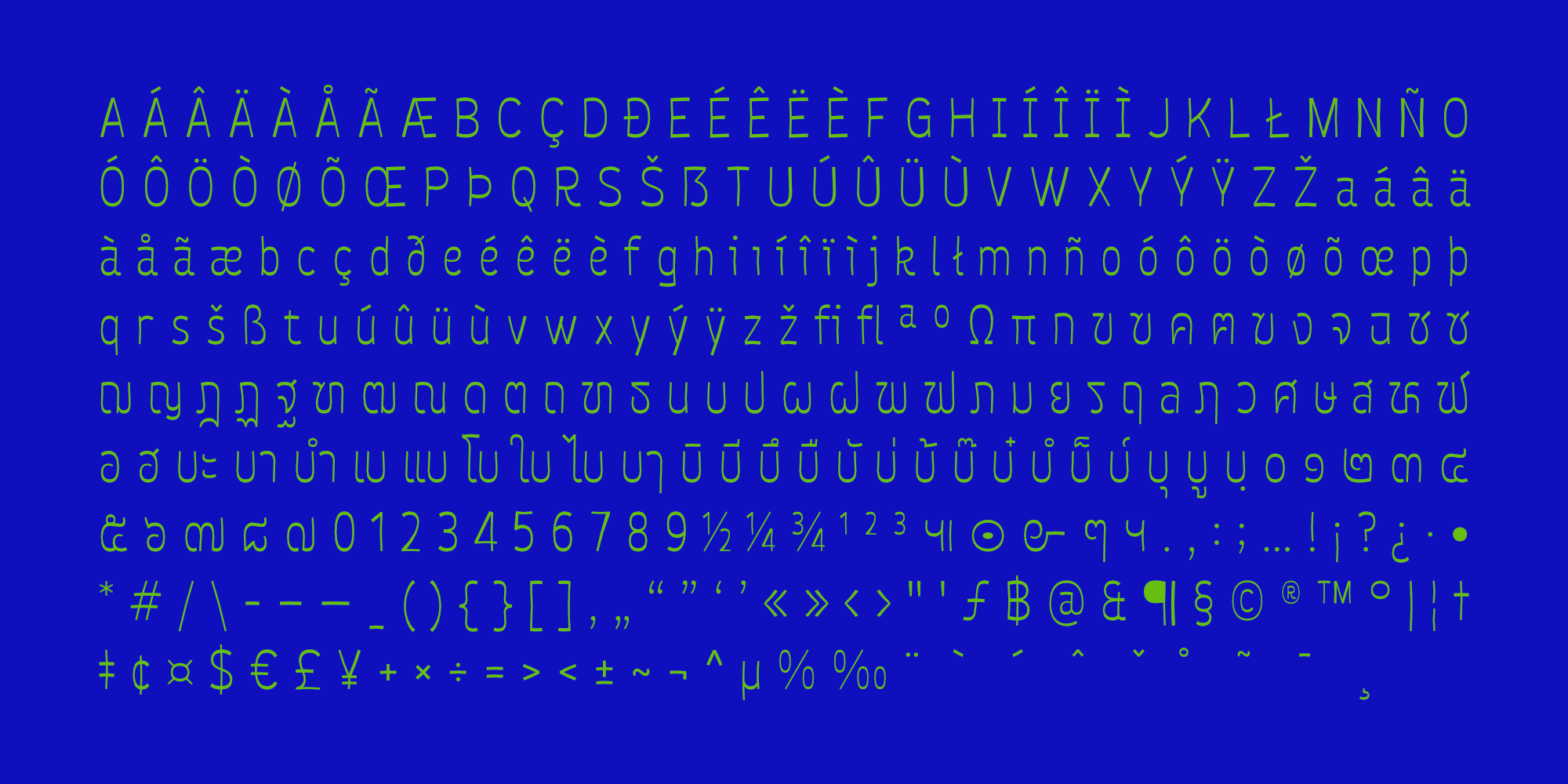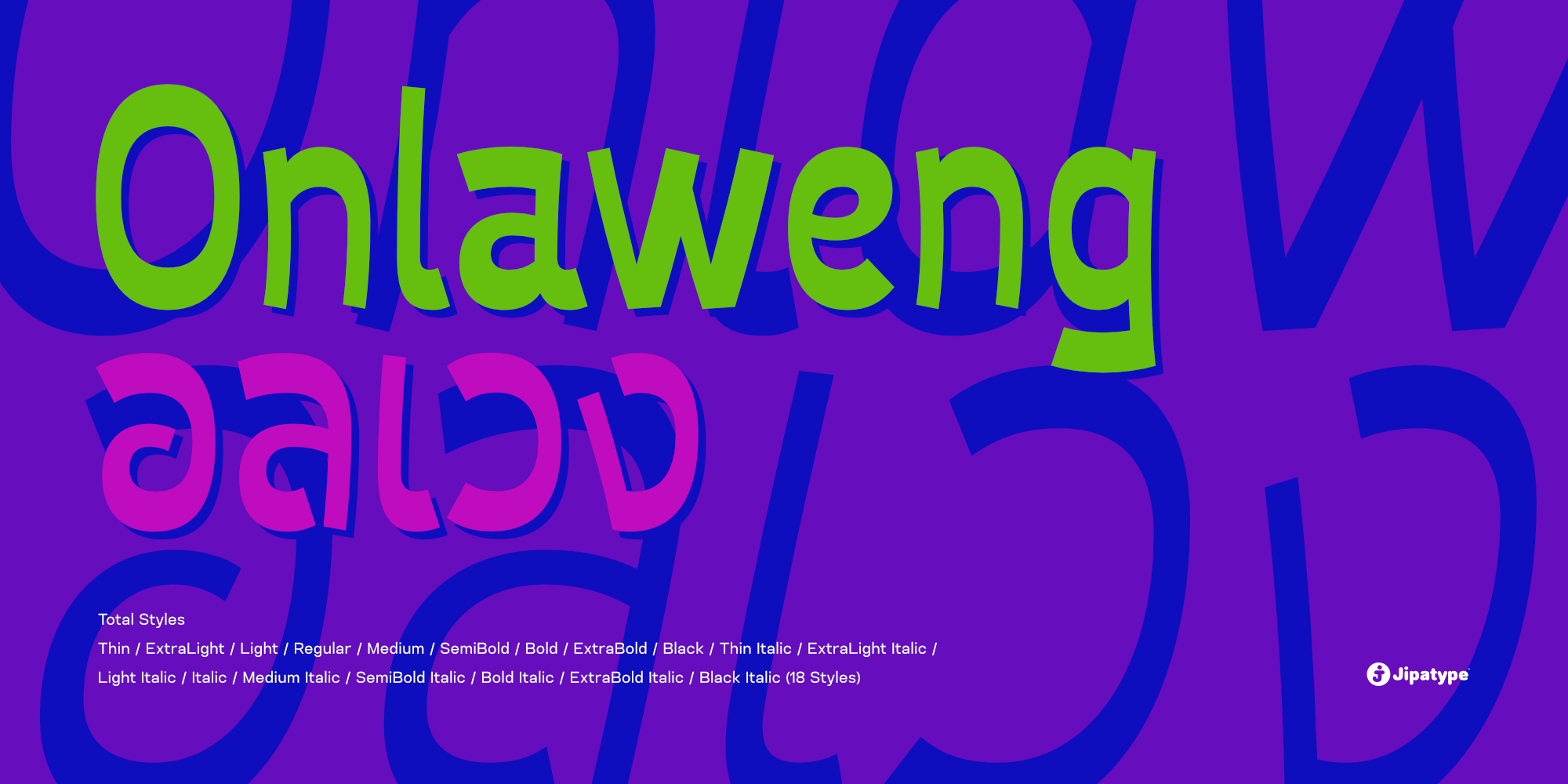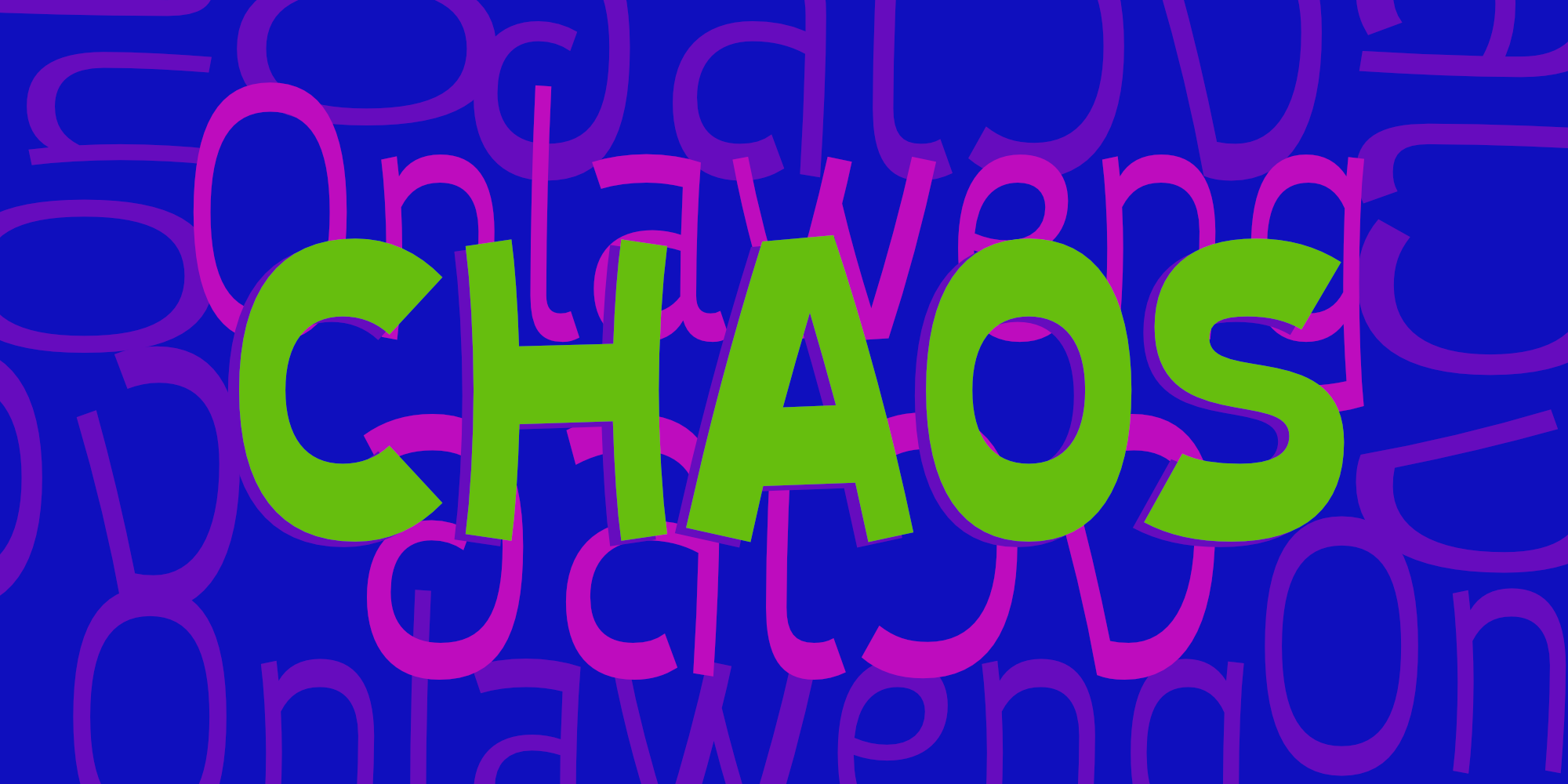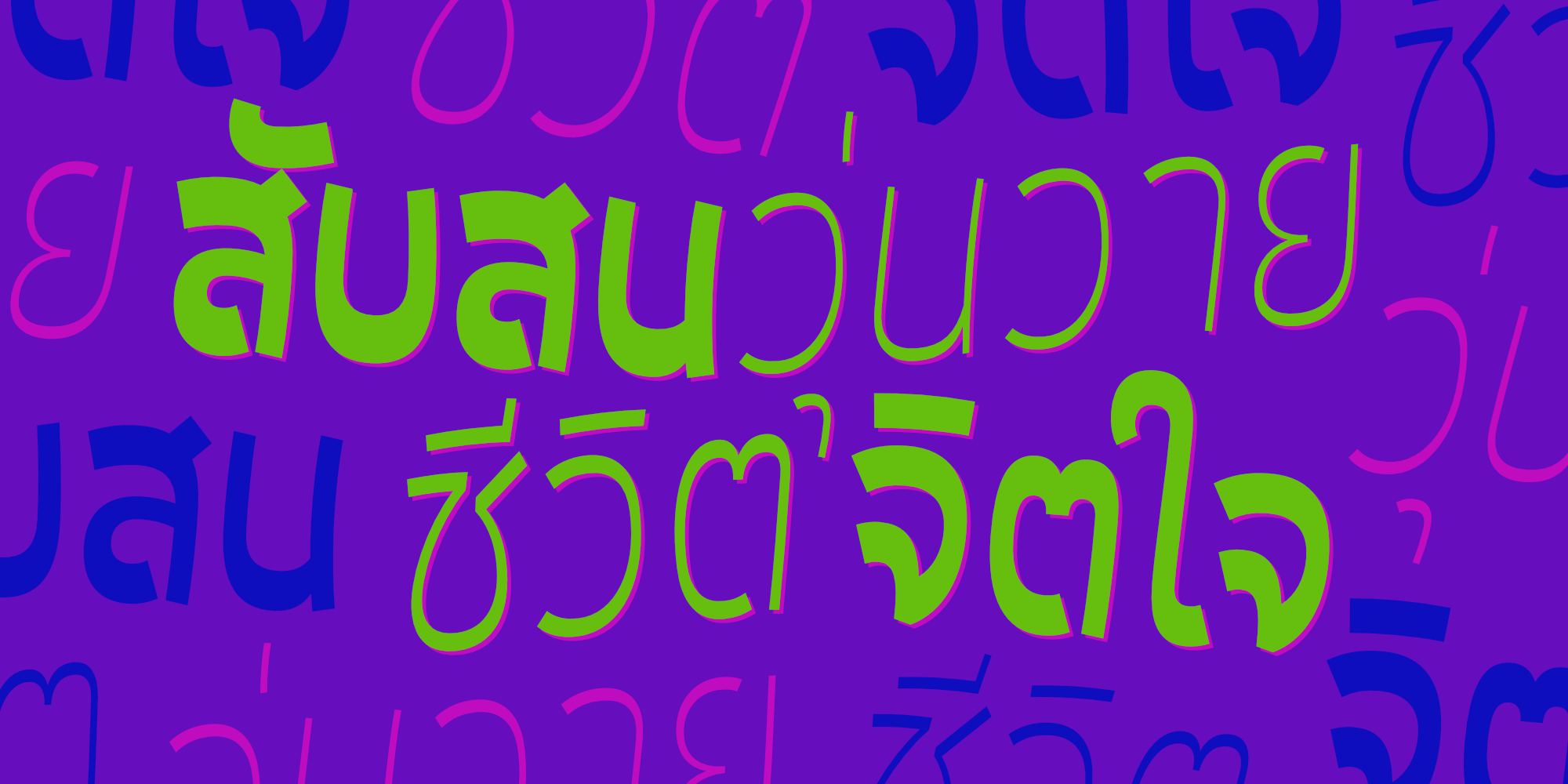
อลเวง | Onlaweng
Onlaweng เป็นแบบอักษรผาดหัว (Display Font) ที่สลับตำแหน่งน้ำหนักของเส้นแนวนอนและแนวตั้ง (Reverse Contrast) และมีโครงสร้างที่ดูแล้วไม่แข็งแรงให้อารมเหมือนเขียนด้วยปากกามาคเกอร์หัวตัด เมื่อรวมองค์ประกอบเหล่านี้เข้าด้วยกันทำให้แบบอักษรนี้ดูแปลกประหลาด และดูสับสน แต่ยังอ่านได้ ด้วยน้ำหนักที่ครอบคลุมการใช้งานถึง 18 สไตล์ ตั้งแต่ Thin ไปจนถึง Black พร้อมตัวเอียง เหมาะอย่างยิ่งสำหรับงานที่ต้องการความออกจากขนบธรรมเนียมแบบเดิม ๆ